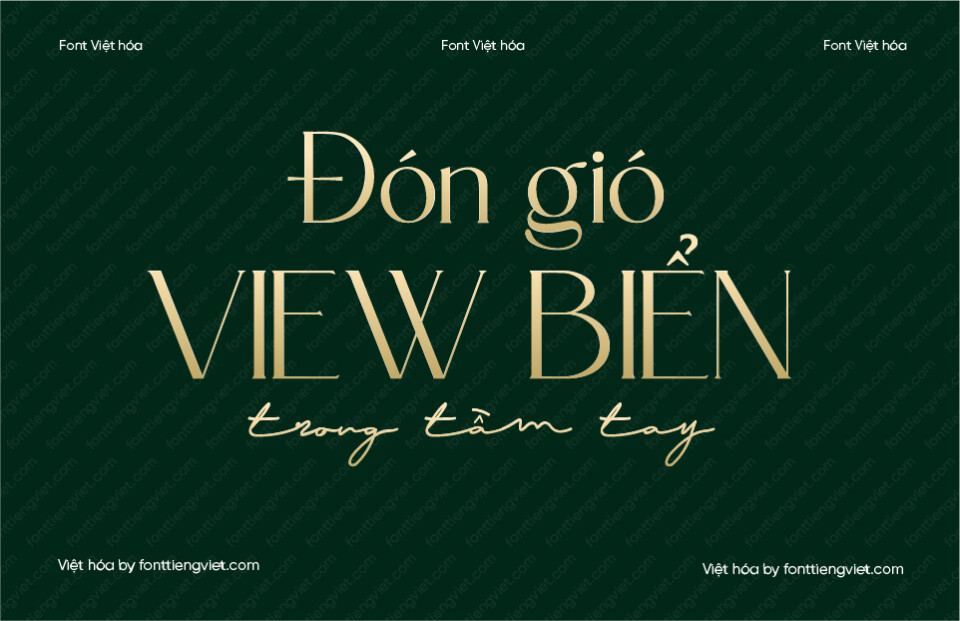
Font Việt hóa 1FTV VIP Borish – Font bất động sản, font spa thẩm mỹ
Font Việt hóa 1FTV VIP Borish – Font bất động sản, font spa thẩm mỹ đẳng cấp và sang trọng
Trong thế giới thiết kế đồ họa chuyên nghiệp, việc lựa chọn một bộ Font Miễn Phí chất lượng luôn là ưu tiên hàng đầu của các designer. Đặc biệt đối với các lĩnh vực đòi hỏi sự tinh tế và đẳng cấp cao như bất động sản hay làm đẹp, Font Việt hóa 1FTV VIP Borish – Font bất động sản, font spa thẩm mỹ nổi lên như một giải pháp hoàn hảo. Đây là bộ font được tinh chỉnh kỹ lưỡng, mang phong cách hiện đại nhưng vẫn giữ được nét thanh lịch cần thiết để làm nổi bật giá trị thương hiệu. Việc sử dụng đúng font chữ không chỉ giúp truyền tải thông điệp hiệu quả mà còn tạo dựng niềm tin tuyệt đối với khách hàng ngay từ cái nhìn đầu tiên qua các ấn phẩm quảng cáo.
Tại sao nên chọn Font Việt hóa 1FTV VIP Borish – Font bất động sản, font spa thẩm mỹ cho thiết kế?
Bộ font này được thiết kế với những đường nét sắc sảo, có sự cân bằng tuyệt vời giữa độ dày và độ mảnh. Điều này giúp các thiết kế liên quan đến căn hộ cao cấp, biệt thự hay các dự án nghỉ dưỡng trở nên uy tín và giá trị hơn. Đối với ngành làm đẹp, sự mềm mại của các ký tự giúp khách hàng cảm nhận được sự tận tâm và chuyên nghiệp của dịch vụ spa hay thẩm mỹ viện.
Sự linh hoạt trong ứng dụng thực tế
Font Việt hóa 1FTV VIP Borish – Font bất động sản, font spa thẩm mỹ có khả năng ứng dụng cực kỳ đa dạng. Bạn có thể sử dụng nó cho các tiêu đề chính trên website, làm logo thương hiệu, hoặc trình bày trong các catalogue giới thiệu dự án. Nhờ việc đã được Việt hóa hoàn chỉnh, các nhà thiết kế không còn phải lo lắng về lỗi hiển thị dấu tiếng Việt, giúp quy trình làm việc trở nên trơn tru và tiết kiệm thời gian đáng kể. Font chữ này hỗ trợ đầy đủ các ký tự đặc trưng của tiếng Việt, đảm bảo tính thẩm mỹ đồng nhất trên mọi nền tảng hiển thị từ in ấn đến kỹ thuật số.
Đặc điểm nổi bật của Font Việt hóa 1FTV VIP Borish – Font bất động sản, font spa thẩm mỹ
Điểm thu hút lớn nhất của bộ font này chính là cấu trúc hình học chuẩn xác kết hợp với những đường bo góc tinh tế. Nó tạo ra một cảm giác không gian rộng mở, rất phù hợp với tư duy thiết kế kiến trúc và nội thất. Trong lĩnh vực spa, font chữ này gợi lên sự thư thái, nhẹ nhàng nhưng không kém phần sang trọng, giúp nhận diện thương hiệu trở nên độc bản và khó nhầm lẫn với các đối thủ khác trên thị trường hiện nay.
Tối ưu hóa trải nghiệm người dùng qua kiểu chữ
Một bộ font tốt không chỉ đẹp mà còn phải dễ đọc. Font Việt hóa 1FTV VIP Borish – Font bất động sản, font spa thẩm mỹ đáp ứng xuất sắc tiêu chí này với khoảng cách giữa các chữ cái được tính toán khoa học. Điều này đặc biệt quan trọng khi bạn trình bày các bảng báo giá bất động sản hoặc danh mục dịch vụ thẩm mỹ, nơi thông tin cần được tiếp nhận một cách nhanh chóng và rõ ràng nhất. Sự kết hợp giữa tính nghệ thuật và tính ứng dụng đã biến nó trở thành lựa chọn hàng đầu cho các chiến dịch marketing cao cấp.
Lời kết về bộ Font Việt hóa 1FTV VIP Borish – Font bất động sản, font spa thẩm mỹ
Tóm lại, nếu bạn đang tìm kiếm một công cụ để tạo nên sự khác biệt cho các dự án của mình, đừng bỏ qua Font Miễn Phí, Font Việt Hóa, Font Việt hóa 1FTV VIP Borish – Font bất động sản, font spa thẩm mỹ. Với sự kết hợp hoàn hảo giữa thẩm mỹ và tính năng, bộ font này chắc chắn sẽ làm hài lòng ngay cả những khách hàng khó tính nhất. Hãy trải nghiệm ngay sức mạnh của ngôn từ thông qua những đường nét chữ tuyệt đẹp này để khẳng định đẳng cấp thương hiệu Việt trên bản đồ thiết kế chuyên nghiệp. Đây chính là chìa khóa để mở ra những thành công mới trong lĩnh vực bất động sản và làm đẹp đầy tiềm năng.